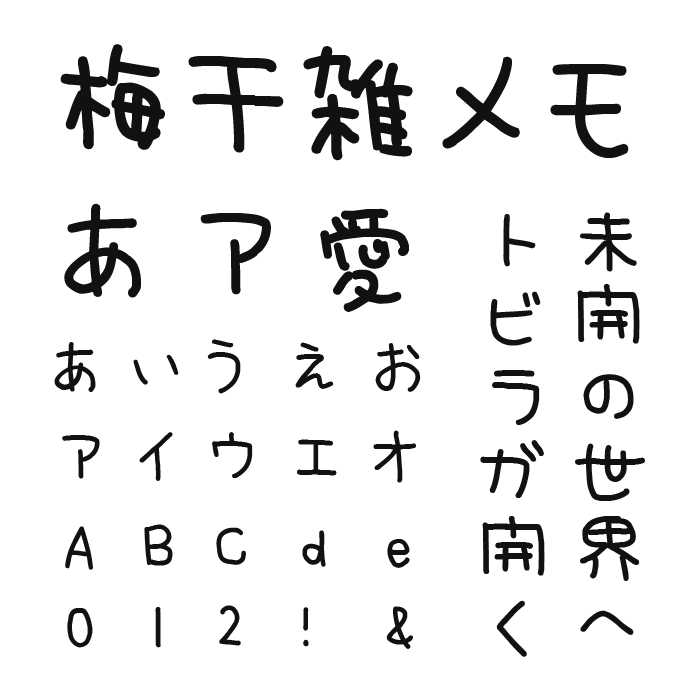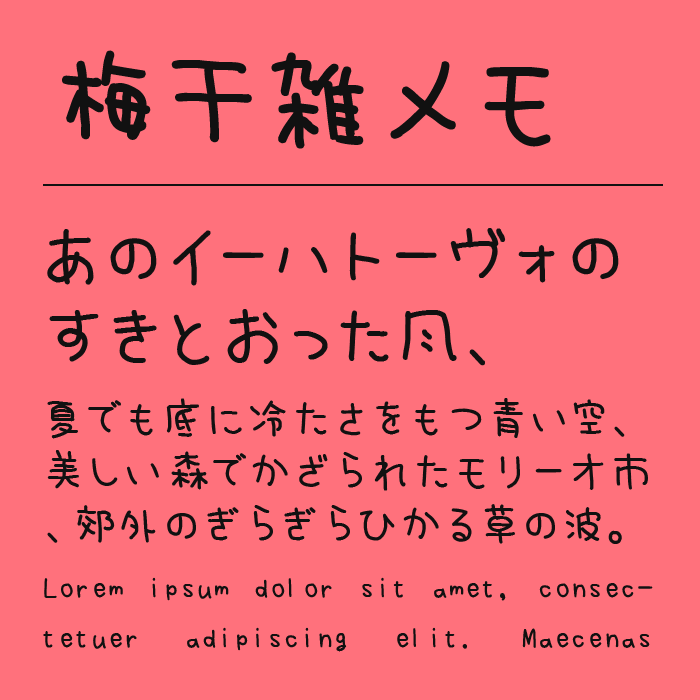
梅干雑メモフォントは、油性ペンやサインペンでメモを書いたような、素朴で少しラフな手書きフォントです。
線にはほどよい太さがありながら、文字の形はきっちり揃えすぎておらず、「雑に書いた」という名前の通り、気負わない手書き感が残されています。
買い物メモや手帳、付箋、レシピ、日記風のデザインなど、日常のちょっとした文章を見せる場面に使いやすそうです。手書きフォントの中では比較的読みやすく、短い文章だけでなく、ある程度まとまったテキストにも合わせやすい印象です。きれいすぎない文字だからこそ、人が実際に書いたような親近感があります。
収録文字は、漢字・ひらがな・カタカナ・アルファベット・数字・記号が収録。